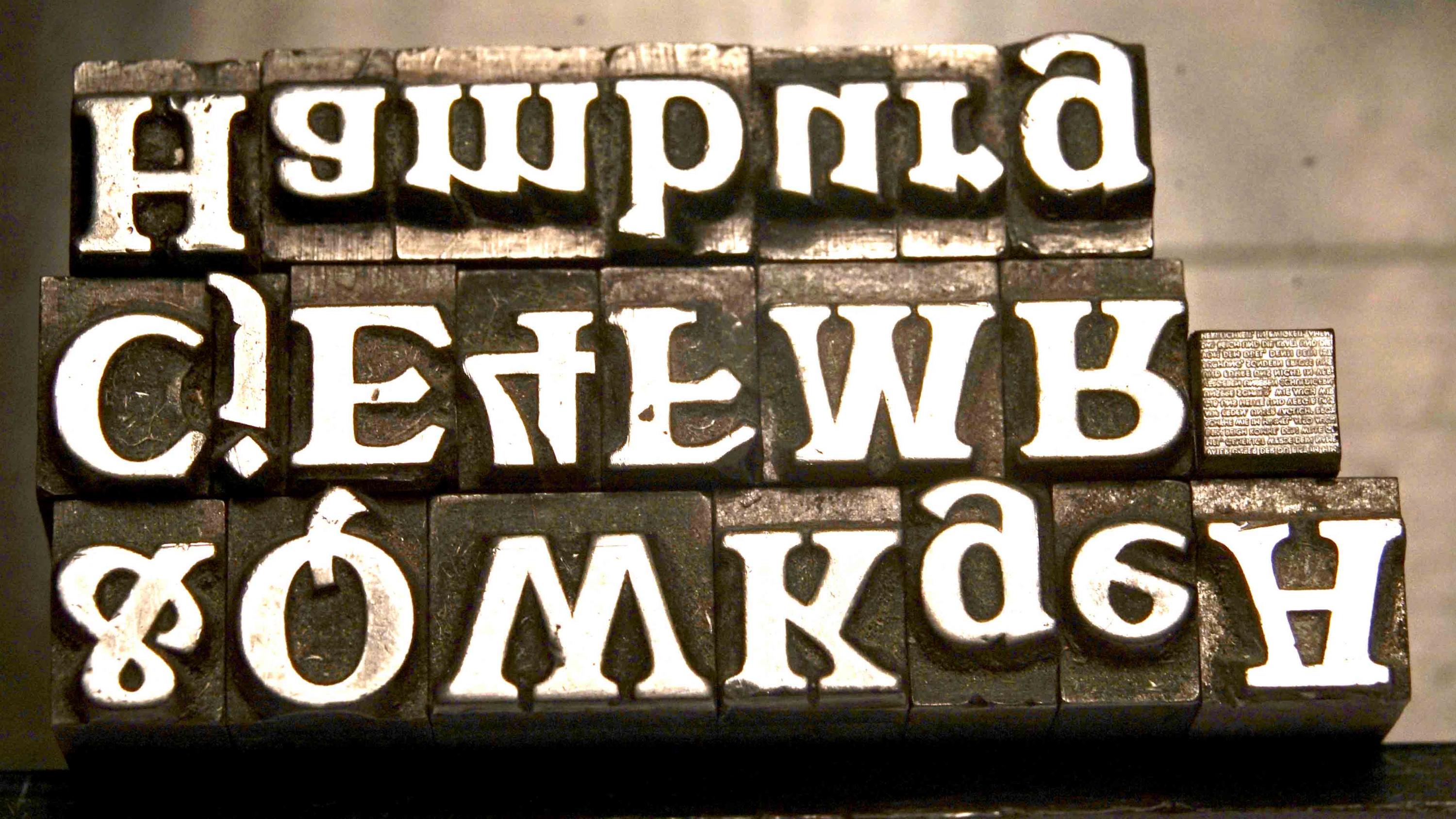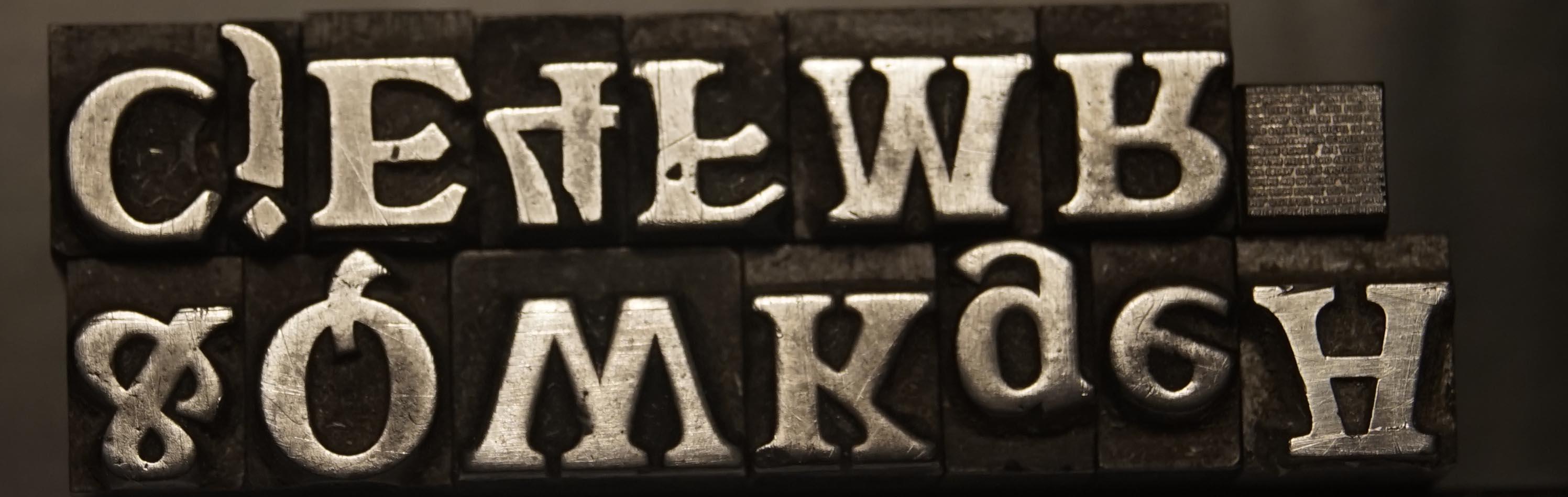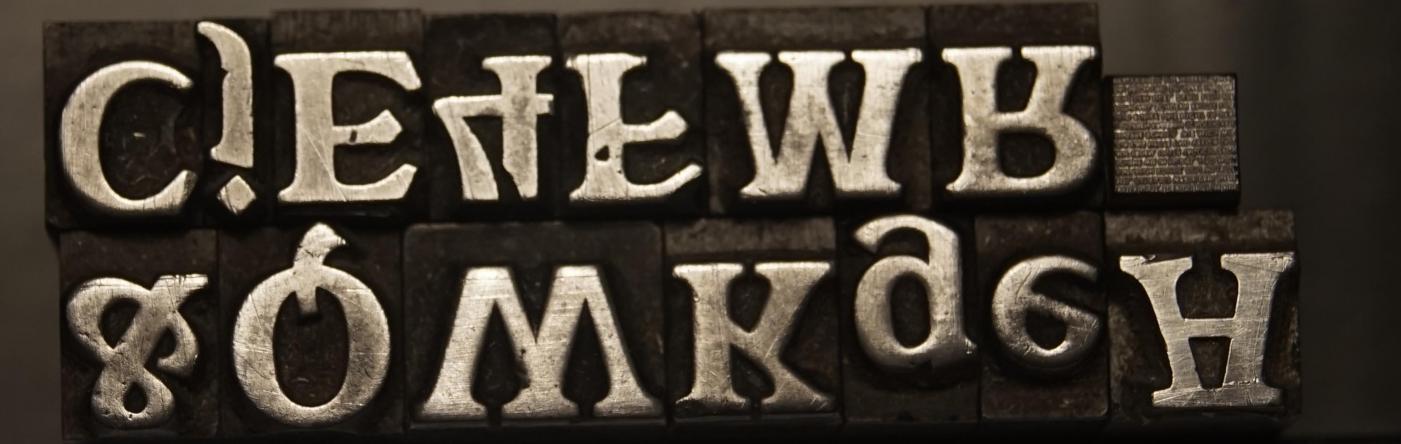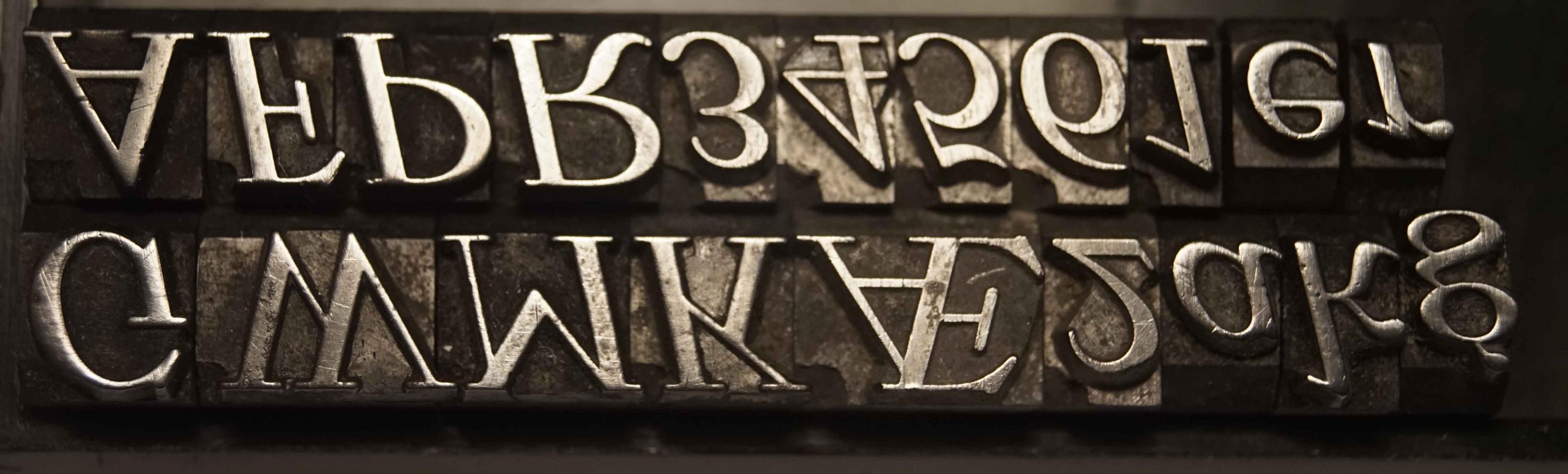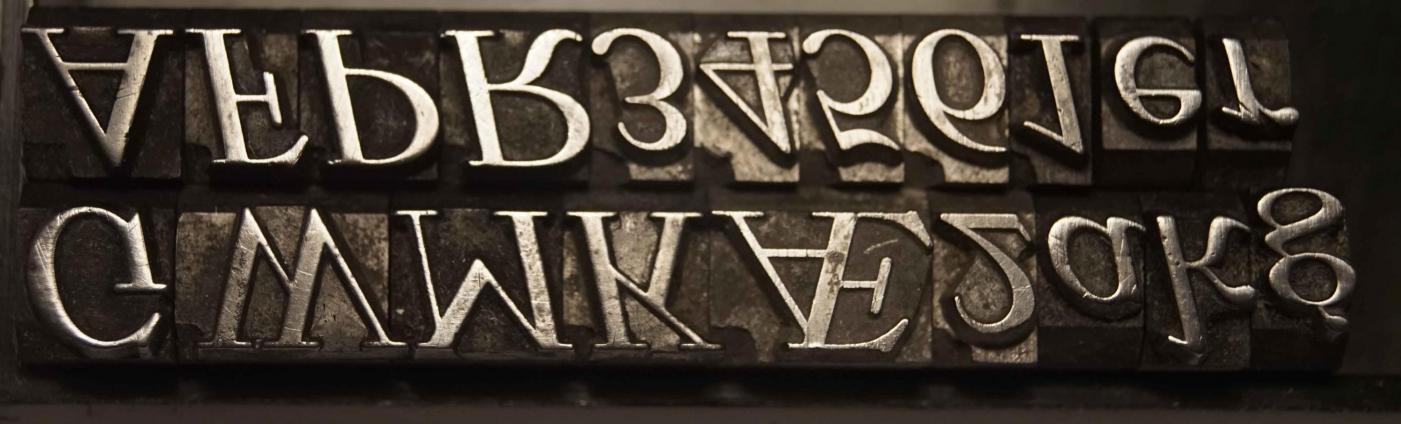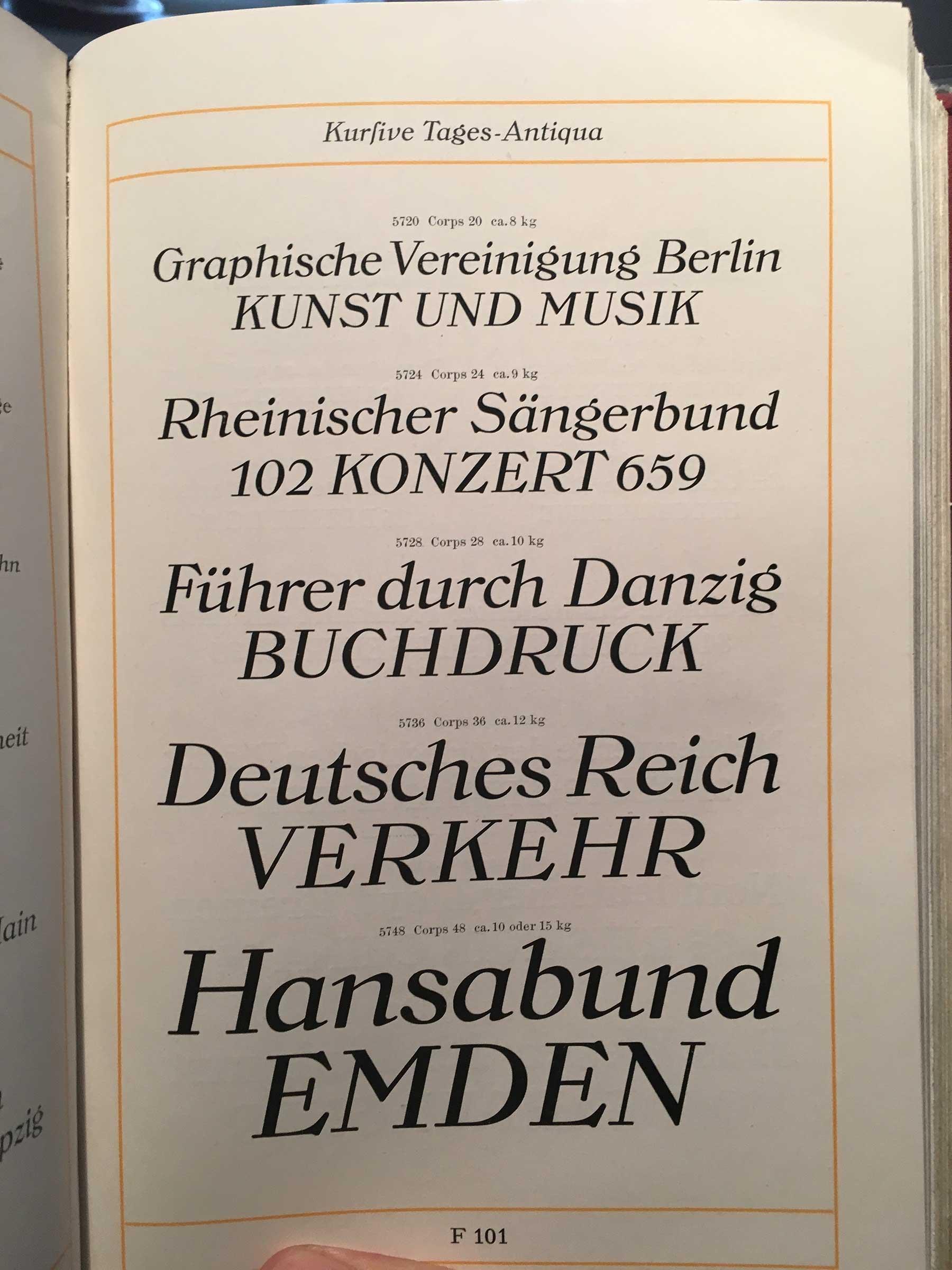
Bleisatzschrift unbekannt
Bin gerade dabei mir eine kleine Bleisatzwerkstatt im Keller einzurichten. Habe vor kurzem ein Konvolut an Schriften gekauft und verzweifle schier an der Identifikation dieser beiden Schriften. Kann jemand helfen? Desweiteren bin ich interessiert an Foren die evtl. auch Tauschbörsen beinhalten. Habe inzwischen von allem etwas (AG, Futura, Neuzeit, Folio etc.), möchte aber lieber in möglichst kompletten Familien arbeiten. Bin für jeden Hinweis dankbar. Bin übrigens gelernter Setzer (Bleisatz).
Die untere Schrift könnte die kursive Tages-Antiqua sein. Ist aber nur eine Vermutung, da mir kein Vergleichsmuster vorliegt.
Nachdem die obere Schrift ziemlich abgescheuert aussieht, gewinnt sie doch einen ganz eigenen Reiz. ich würde so ein altes Kampfross nicht zum Schlächter führen. Das richtige Papier, die passende Gestaltung, daraus läßt sich was Schönes machen.
Bei der oberen Schrift handelt es sich wahrscheinlich um die halbfette "Grimm-Antiqua". 1938, W. Woellmers Schriftgießerei, Berlin.
Tages Antiqua passt, ist ziemlich gut ausgebaut, sogar mit langem »S«. Grimm passt offenbar auch, denke dass es die fette Variante ist. Klar ist sie »rund«, aber sind wir das nicht alle, wenn wir in die Jahre gekommen sind? Habe jetzt im Netz die magere Variante gesehen, wunderschön, ein kühnes Versal A, und ein Hauch Jugendstil. Gerstenberg kenne ich, war schon in Darmstadt im Museum. Allerdings bin ich jetzt nicht bereit für dieses Hobby viel Geld für gußfrische Schriften auszugeben. Bleisatzmagazin habe ich auf dem Schirm, ist im Moment aber nicht das dabei was ich suche. Habe immer noch Interesse an einer Tauschbörse, da ich zu viele Grotesk-Familien bzw. Einzelschnitte habe.
Im Anhang auch nochmal »Hamburg«.
La antigüedad diaria debe ser correcta. El otro también debe ser lo suficientemente mayor como para ser incluido en el marinero. Ahora necesitarías el habitual "Hamburgo" para comparar.
Hast du der voll Tages-Antiqua Musterbuch? Ich will eine Wiederbelebung machen!